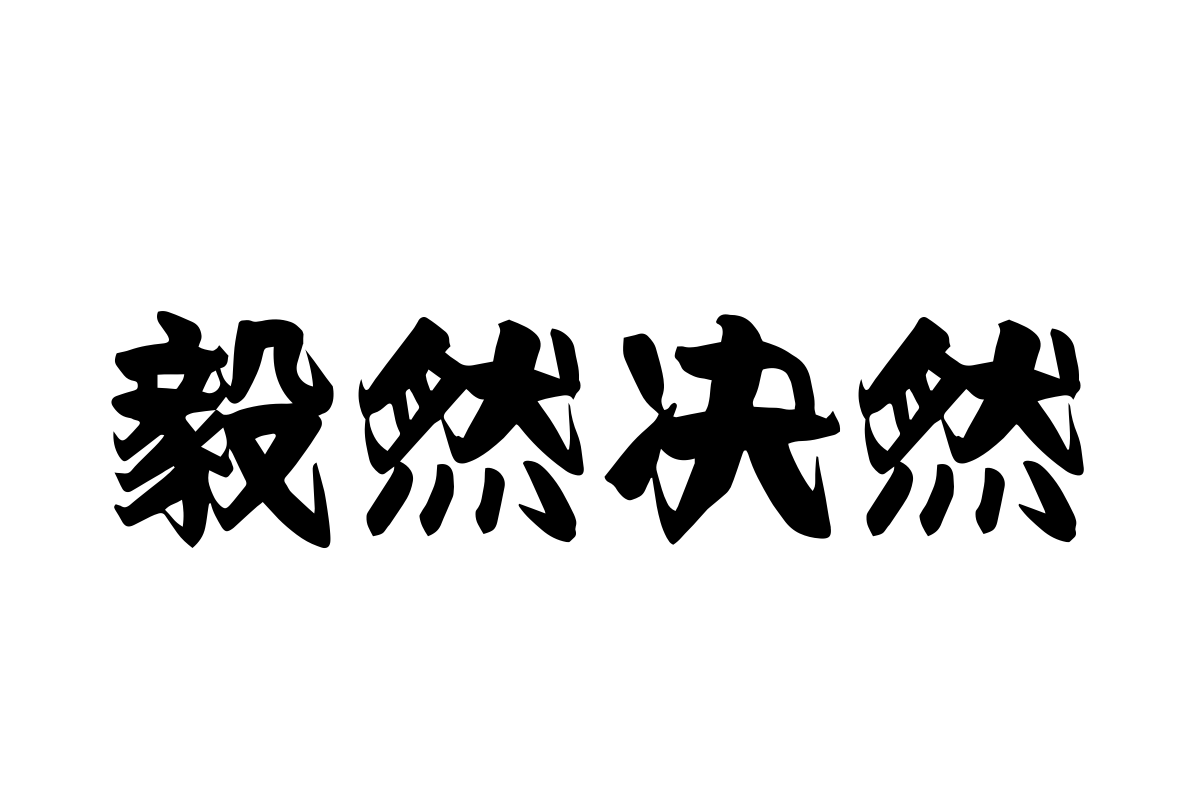
汉仪笔染隐侠是一套具有独特书法风格的字体,由汉仪字库设计。这套字体以其流畅的笔画和独特的结构而受到广泛赞誉。它采用了传统的书法技艺,结合现代设计理念,创造出既传统又现代的视觉效果。
汉仪笔染隐侠字体的特点在于其独特的笔画结构和风格。它的笔画粗细变化丰富,既有粗犷有力的线条,也有细腻柔和的曲线。这种独特的笔画结构使得字体在视觉上具有很强的冲击力和艺术感。同时,这套字体还注重平衡与协调,使得整个字形看起来既和谐又有层次感。
除了外观上的吸引力外,汉仪笔染隐侠字体还具有很高的可读性。它的字形规整,笔画清晰,易于识别和阅读。无论是用于标题、正文还是广告宣传,都能展现出良好的视觉效果和传播效果。
总之,汉仪笔染隐侠是一款具有独特魅力的字体,适合用于各种需要展示个性和艺术性的场合。